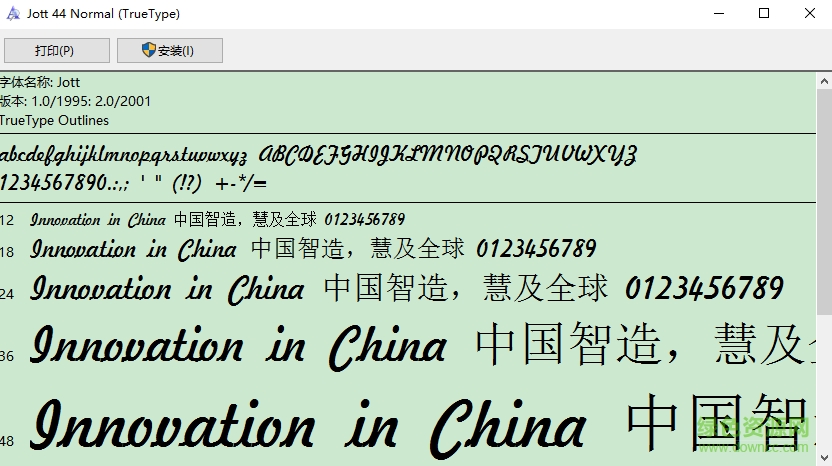
Jott 44 Normal
jott44normal字體是一款非常有特色的藝術(shù)字體,這款英文字體字形優(yōu)美,非常引人入勝,喜歡這款字體的朋友歡迎來綠色資源網(wǎng)下載使用!
Jott 44 Normal字體介紹
Jott 44 Normal是一款應(yīng)用于藝術(shù)設(shè)計方面的英文字體,該字體筆畫正規(guī),可以廣泛應(yīng)用于名片設(shè)計、新聞媒體、宣傳海報、ppt、影視制作以及內(nèi)容用字等領(lǐng)域。
jott44normal字體